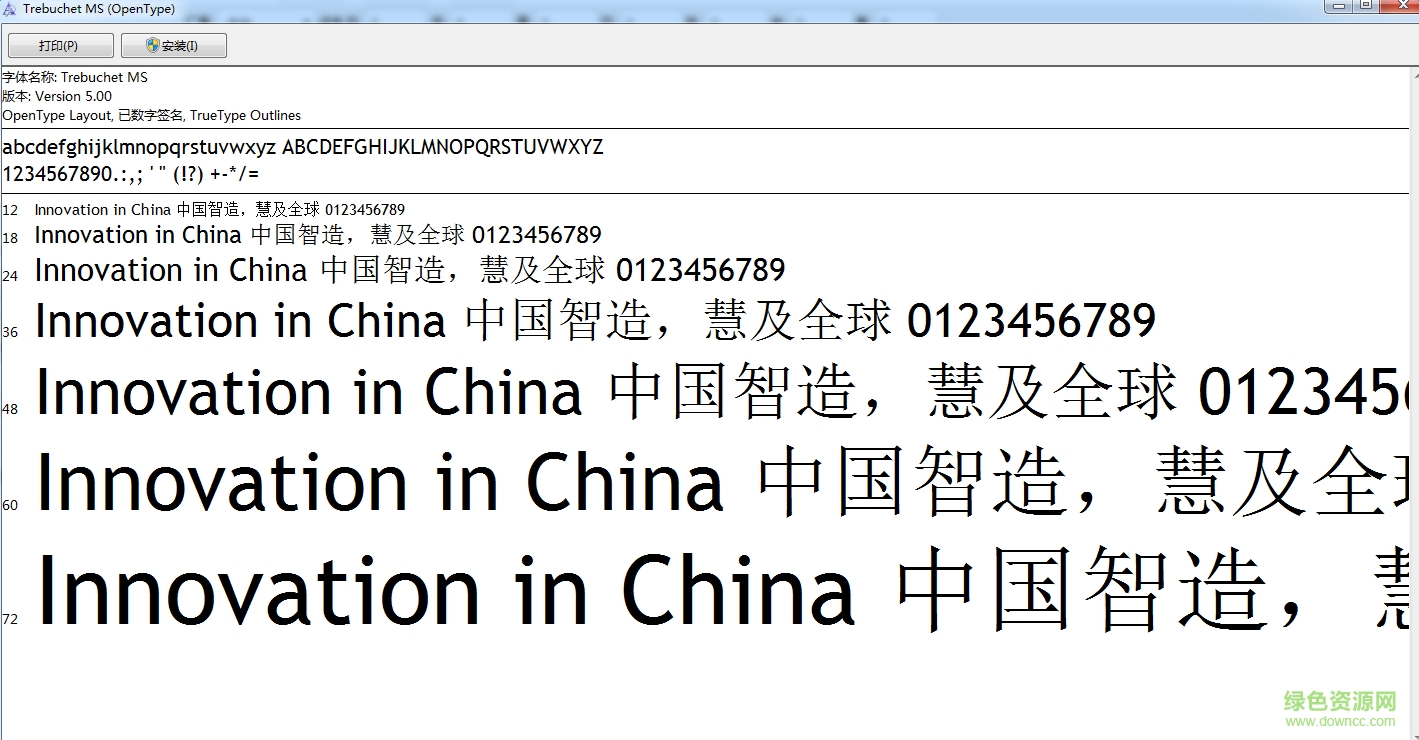
trebuchet ms字體是一款常用于網頁設計的英文體,字體規(guī)范美觀,本站為大家提供Trebuchet MS、Trebuchet MS Italic、Trebuchet MS Bold、Trebuchet MS Bold Italic四款字體,歡迎有需要者前來下載!
Trebuchet MS系列字體是一種無襯線字體,1996年由文生·寇奈爾替微軟開發(fā)。微軟稱Trebuchet MS為良好的網頁設計字體,同時也附載在一些微軟的產品中,包含Microsoft Windows視窗操作系統(tǒng)、Microsoft office套裝軟體以及IE瀏覽器。英文版的Windows XP更是將此字型設為標題列預設字型,